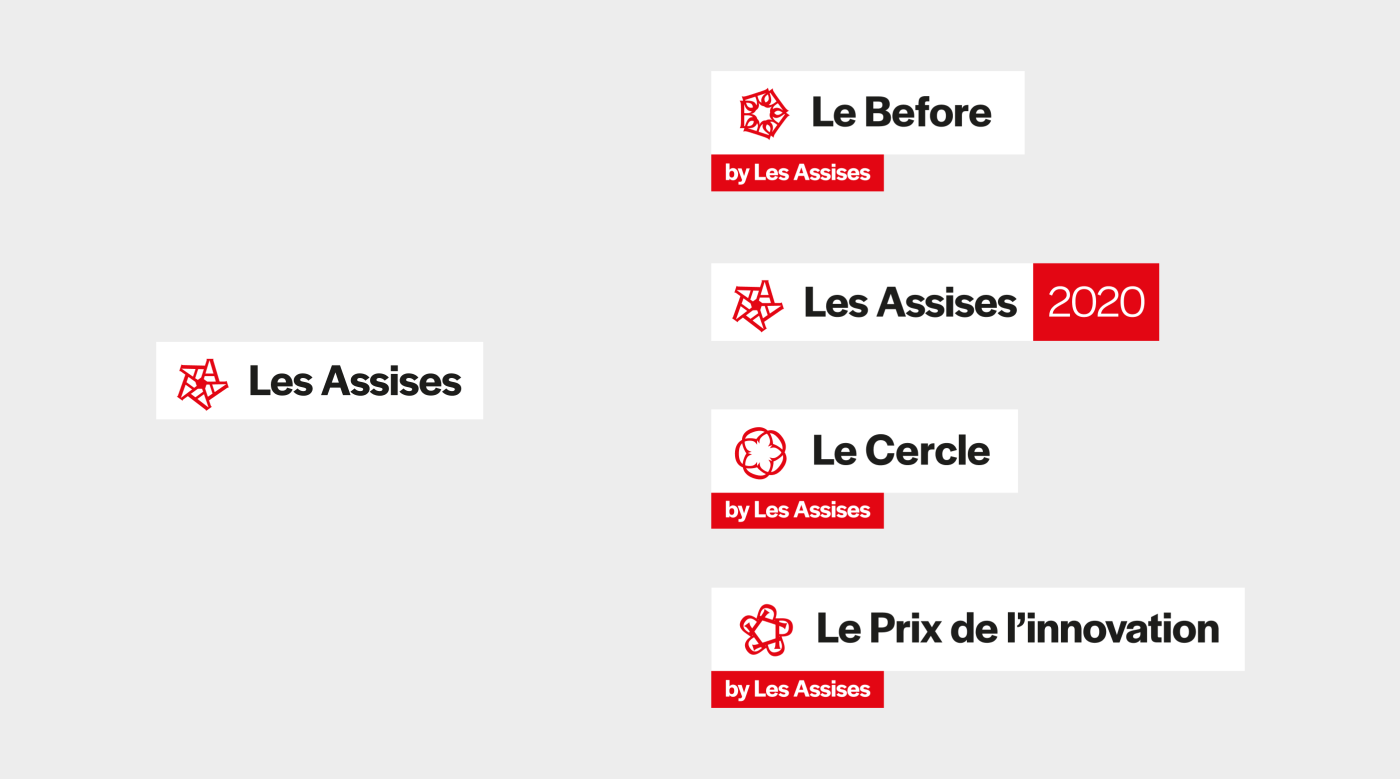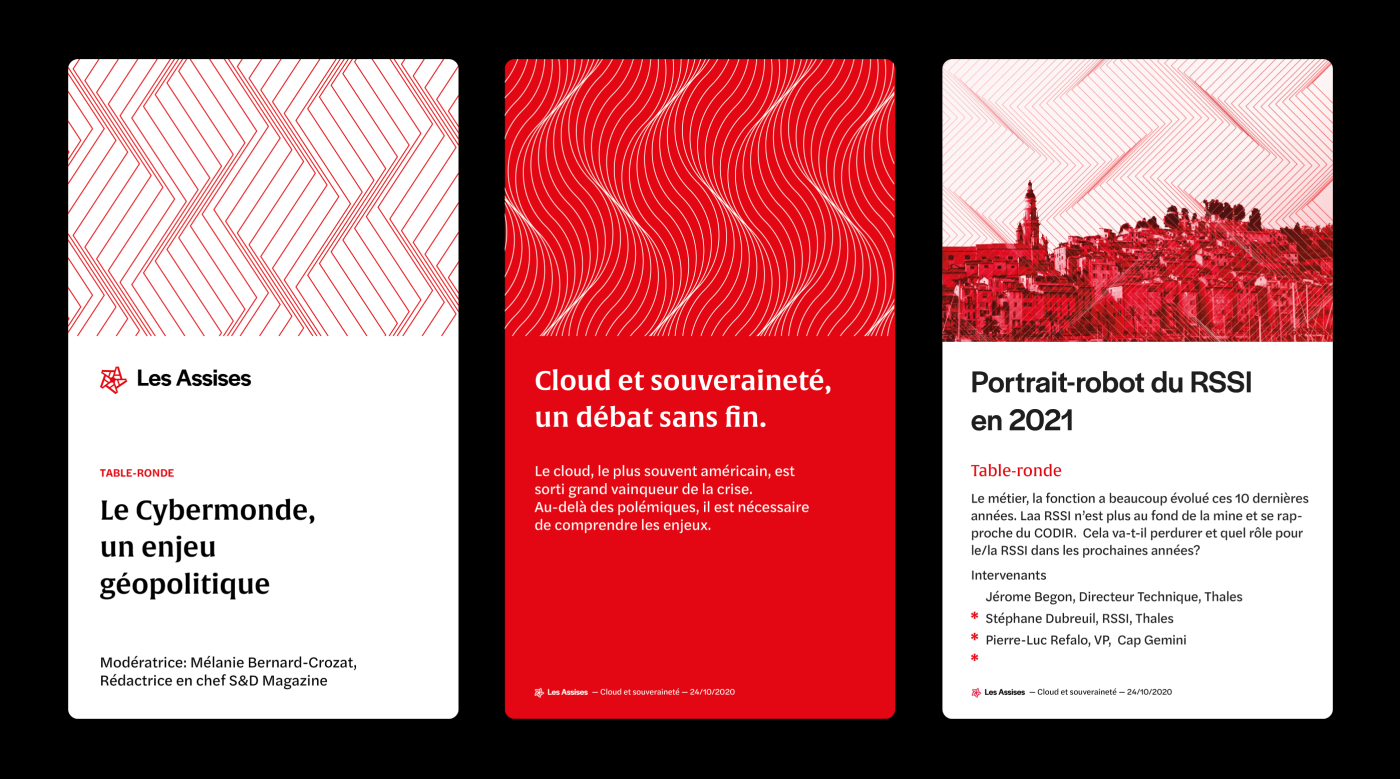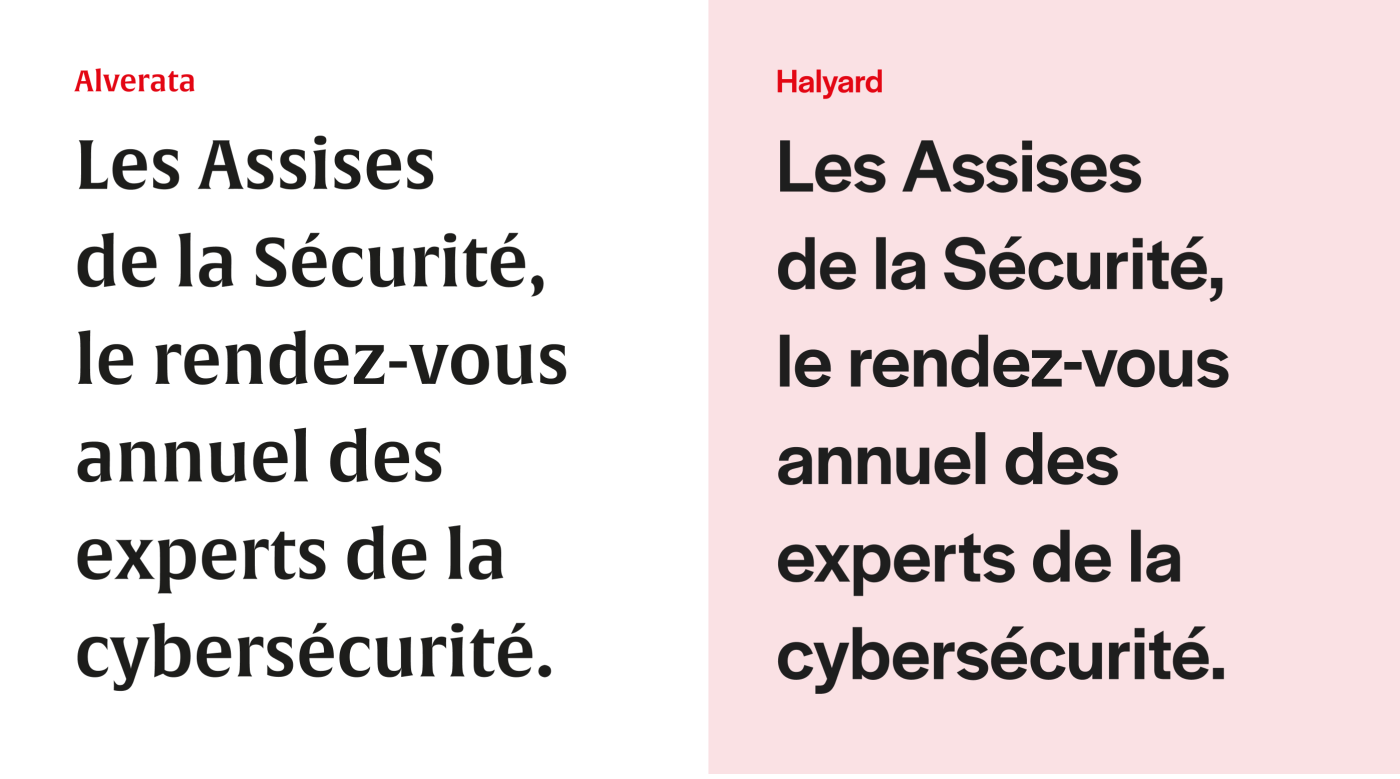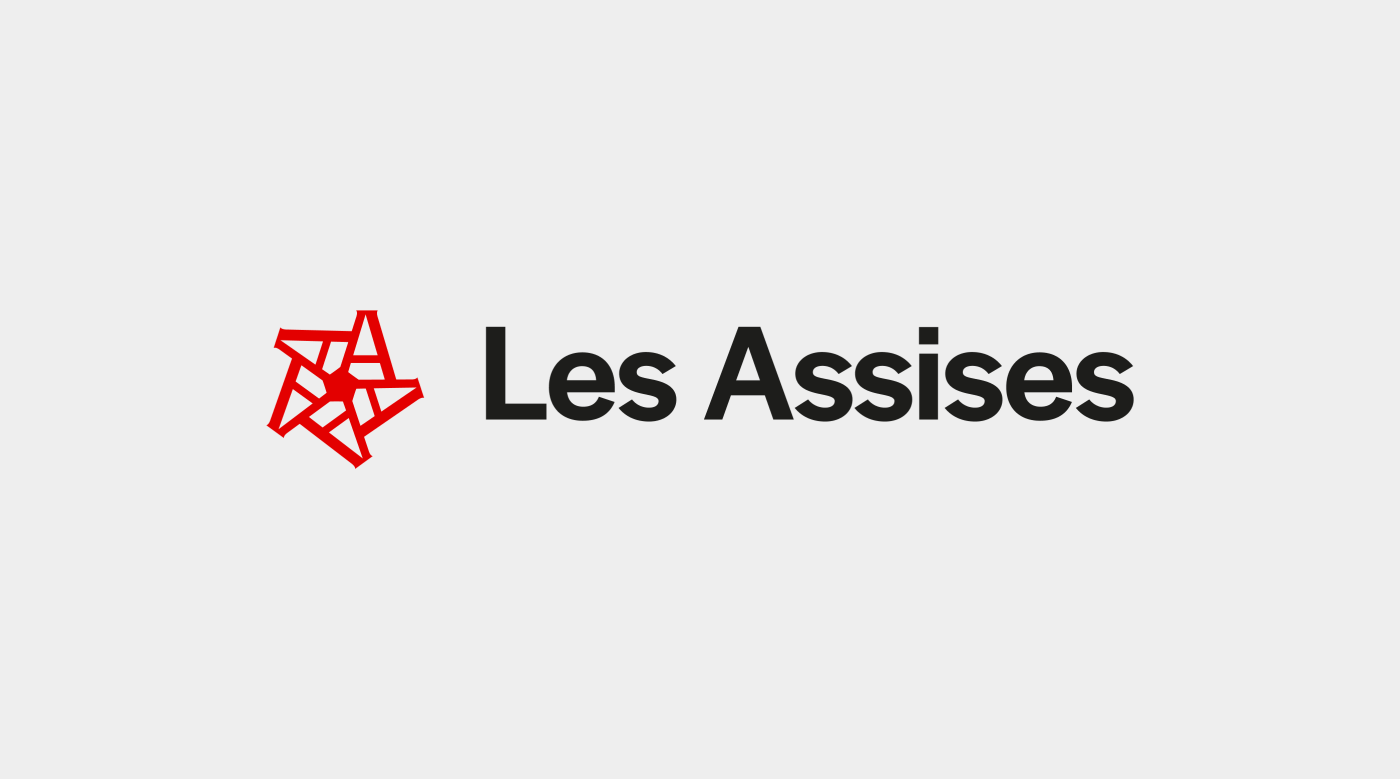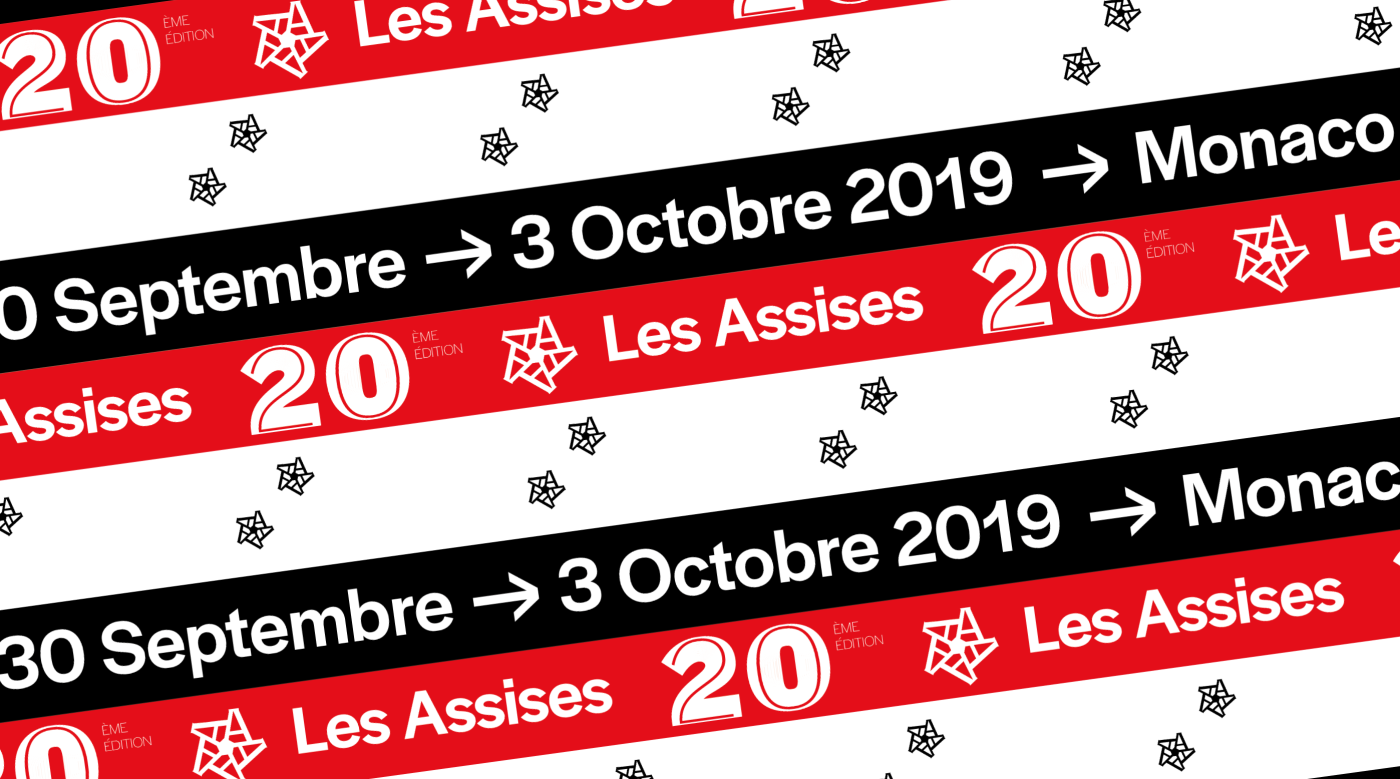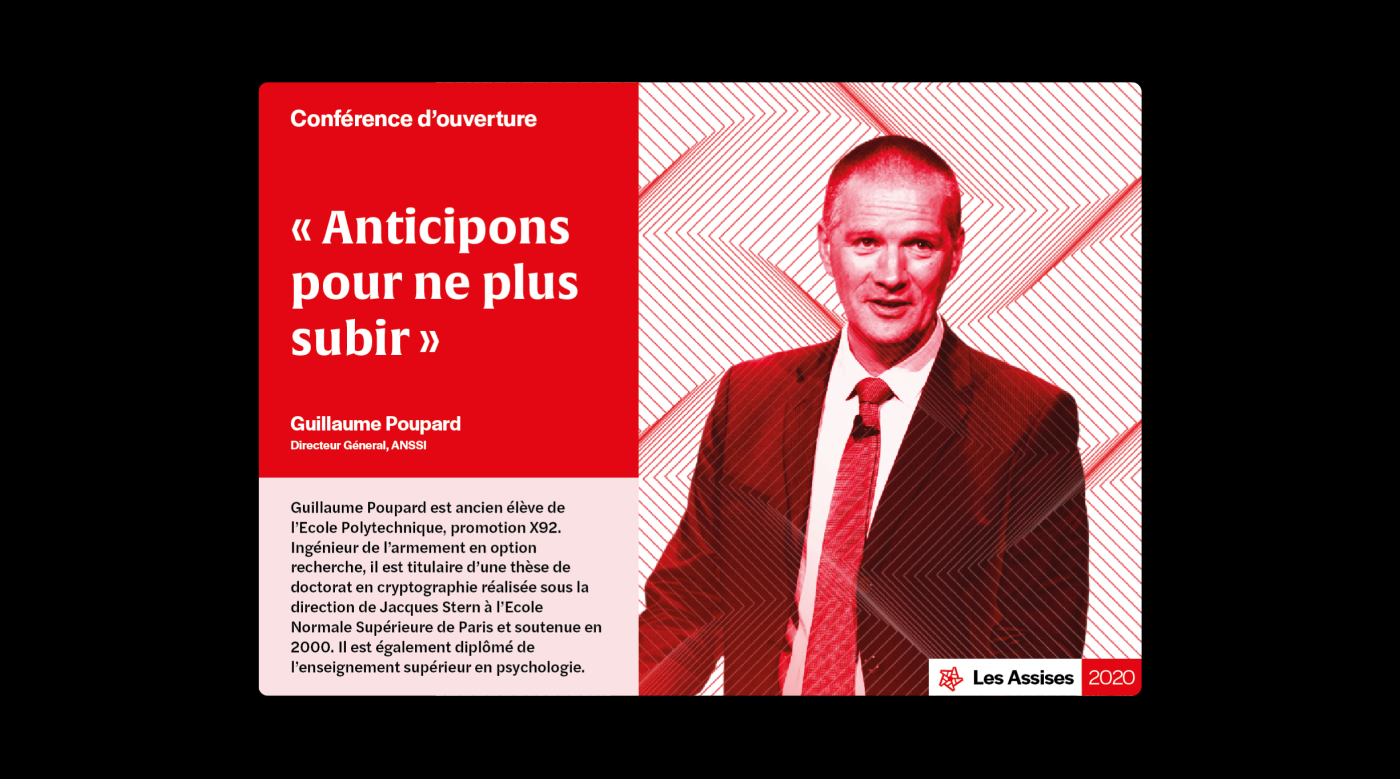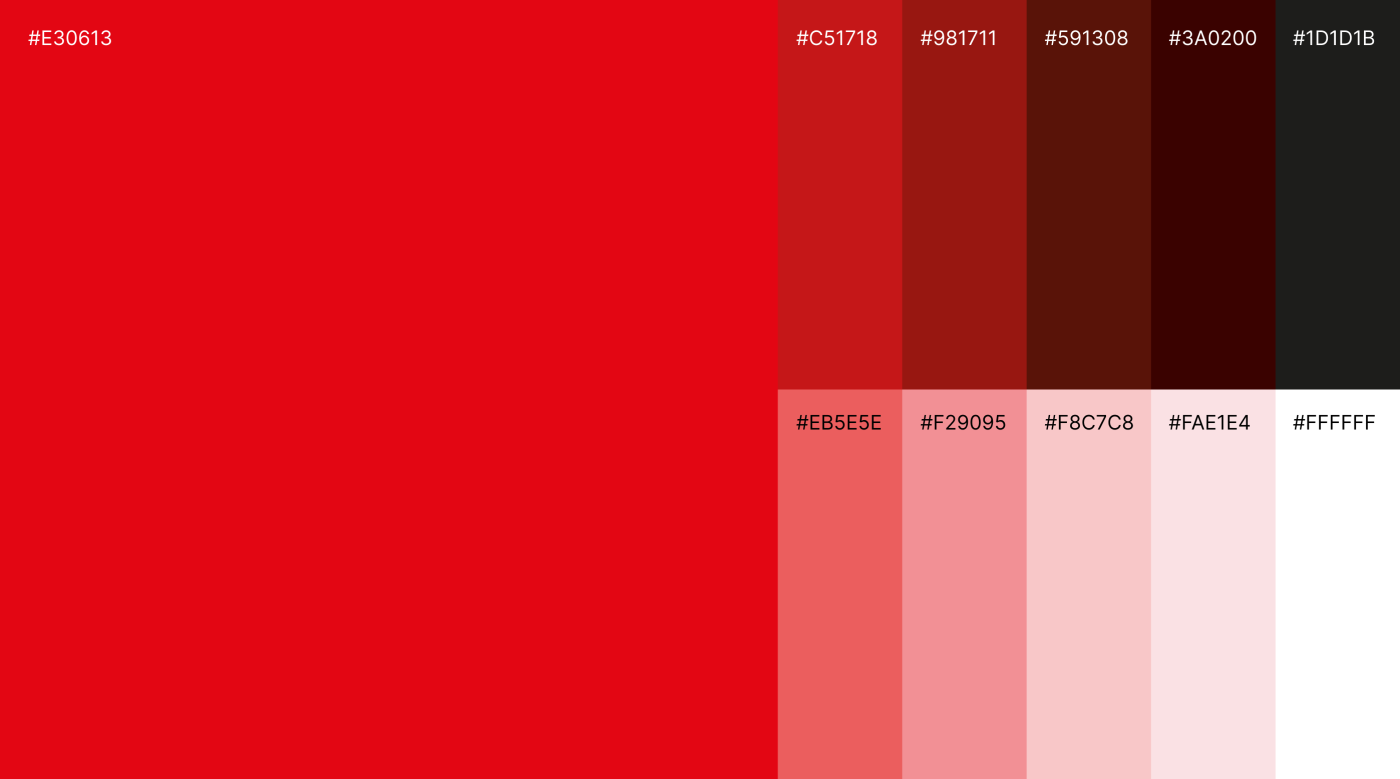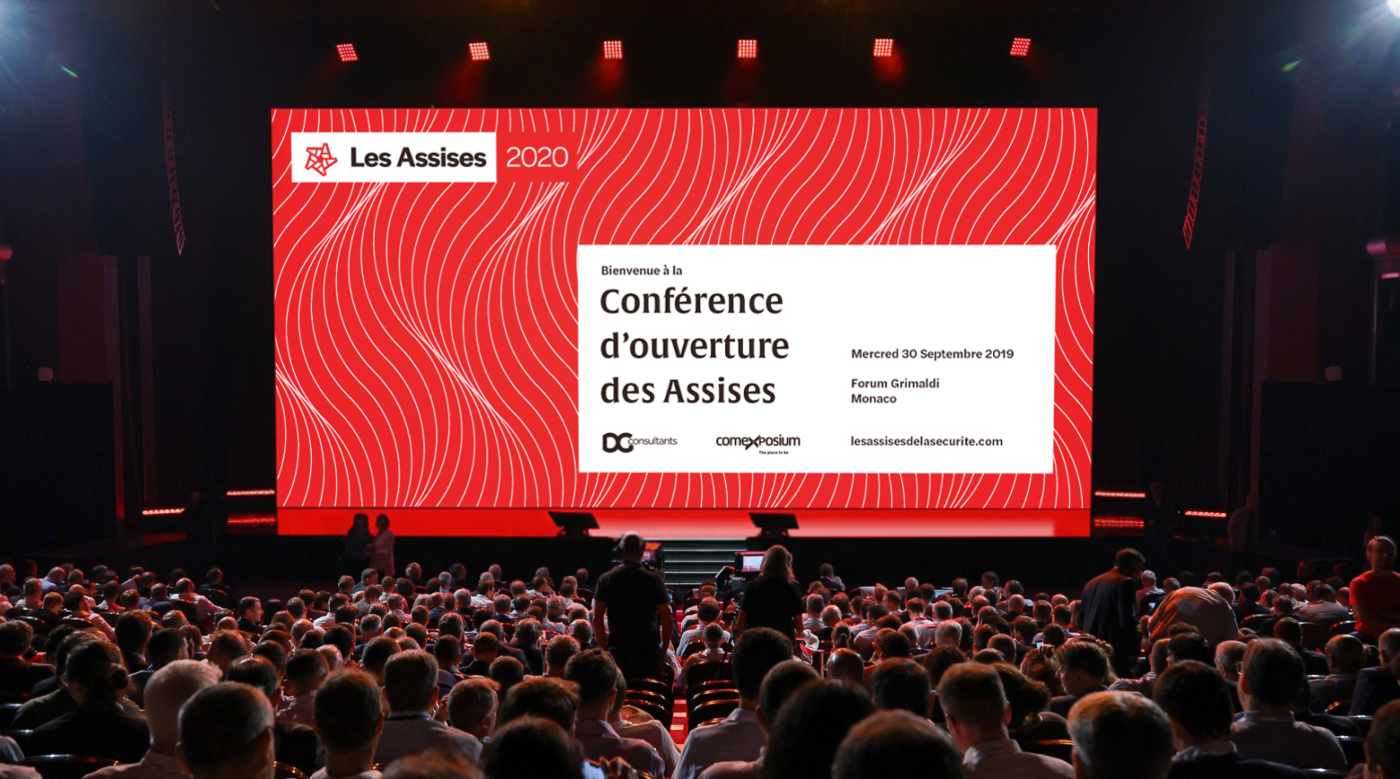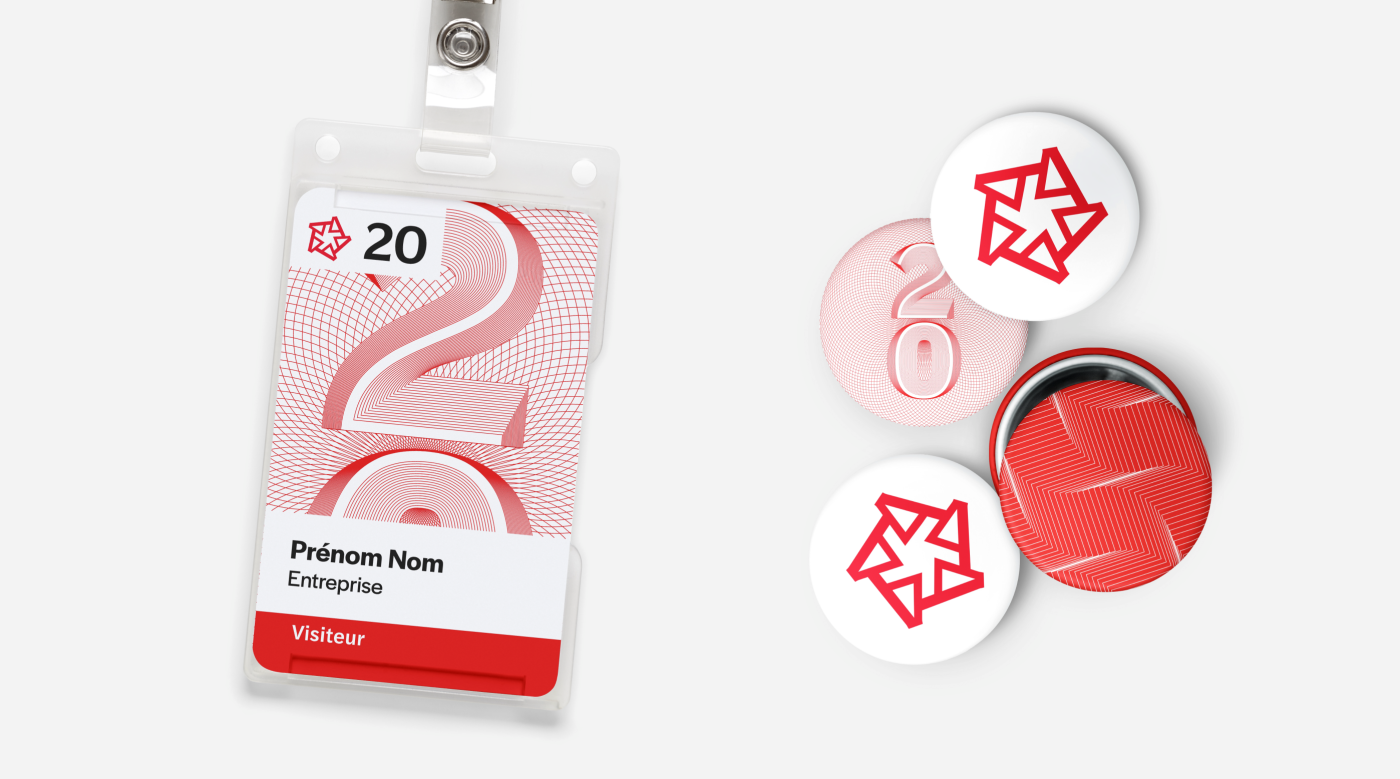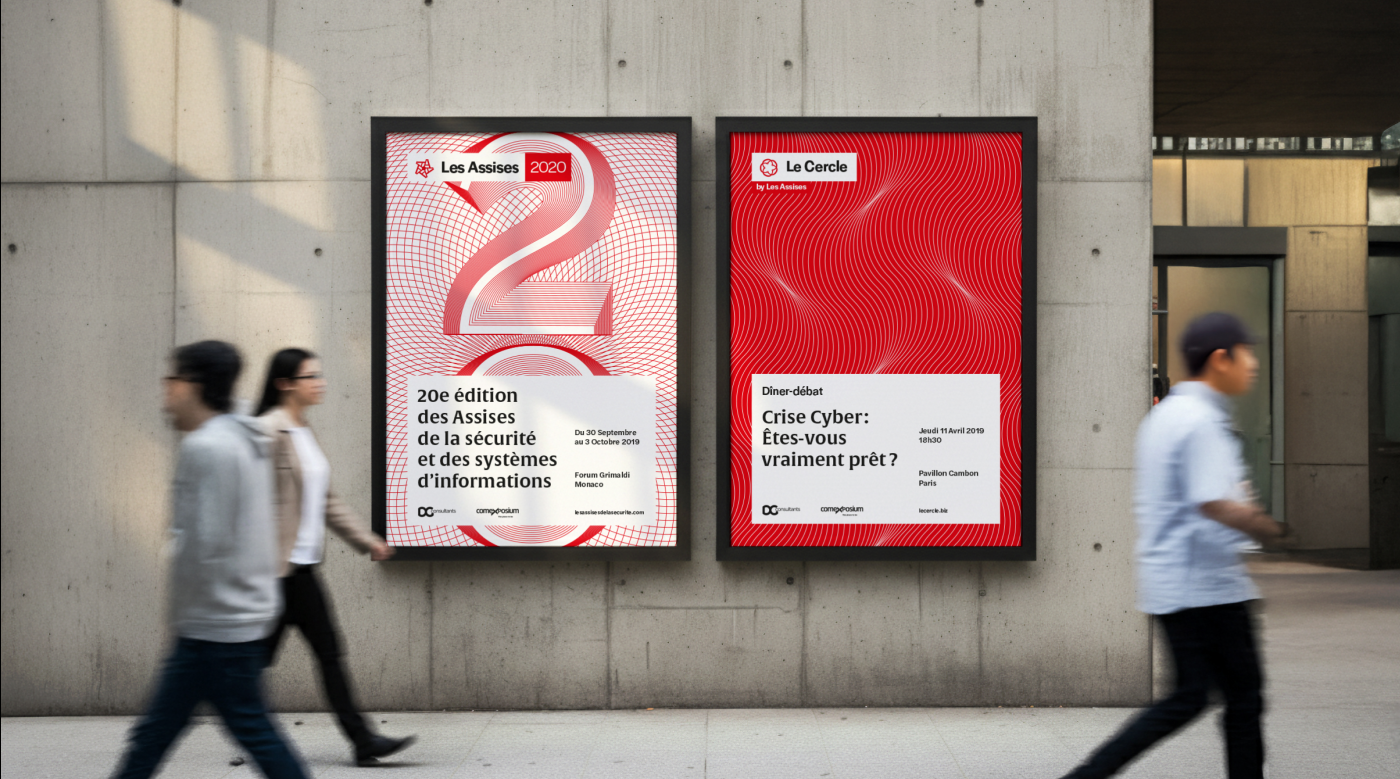
Les Assises
Les Assises de la cybersécurité et des systèmes d'information est un évènement annuel rassemblant les experts du domaine de la cybersécurité.
L'identité visuelle joue avec différents procédés graphiques évoquant la notion de sécurité: guillochage, tramage, sceaux.